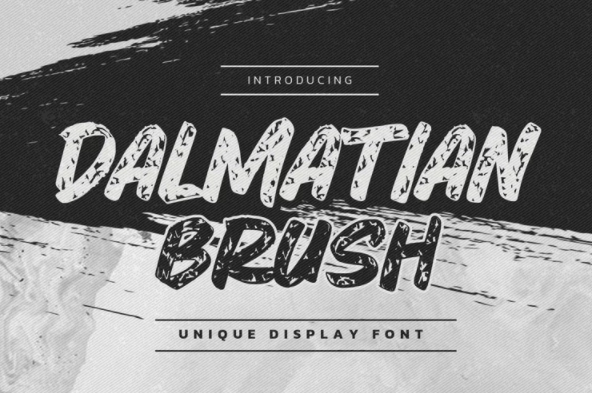
[Fontbundles] Dalmatian Brush Font (2022)
Π’ΠΎΡ‚ ΠΈ наш Π½ΠΎΠ²Ρ‹ΠΉ ΡˆΡ€ΠΈΡ„Ρ‚ Dalmatian Brush это ΡƒΠ½ΠΈΠΊΠ°Π»ΡŒΠ½Ρ‹ΠΉ ΡˆΡ€ΠΈΡ„Ρ‚, ΠΊΠΎΡ‚ΠΎΡ€Ρ‹ΠΉ ΠΏΠΈΡˆΠ΅Ρ‚ΡΡ Π½Π΅ΠΏΡ€ΠΈΠ½ΡƒΠΆΠ΄Π΅Π½Π½ΠΎ ΠΈ быстро. Π­Ρ‚ΠΎ аутСнтичная ΠΊΠΈΡΡ‚ΡŒ ΠΈ ΡΡ‚ΠΈΠ»ΡŒΠ½Ρ‹ΠΉ ΡΡ‚ΠΈΠ»ΡŒ.
Π­Ρ‚ΠΎΡ‚ ΡˆΡ€ΠΈΡ„Ρ‚ создан Π²Ρ€ΡƒΡ‡Π½ΡƒΡŽ с ΠΏΠΎΠΌΠΎΡ‰ΡŒΡŽ кистСй Π² Procreate. Π­Ρ‚ΠΎΡ‚ ΡˆΡ€ΠΈΡ„Ρ‚ ΠΎΡ‚Π»ΠΈΡ‡Π½ΠΎ ΠΏΠΎΠ΄Ρ…ΠΎΠ΄ΠΈΡ‚ для Π²Π°ΡˆΠΈΡ… творчСских ΠΏΡ€ΠΎΠ΅ΠΊΡ‚ΠΎΠ², Ρ‚Π°ΠΊΠΈΡ… ΠΊΠ°ΠΊ водяной Π·Π½Π°ΠΊ Π½Π° Ρ„ΠΎΡ‚ΠΎΠ³Ρ€Π°Ρ„ΠΈΠΈ, ΠΈ идСально ΠΏΠΎΠ΄Ρ…ΠΎΠ΄ΠΈΡ‚ для Π»ΠΎΠ³ΠΎΡ‚ΠΈΠΏΠΎΠ² ΠΈ Π±Ρ€Π΅Π½Π΄ΠΈΠ½Π³Π°, Ρ„ΠΎΡ‚ΠΎΠ³Ρ€Π°Ρ„ΠΈΠΈ, ΠΏΡ€ΠΈΠ³Π»Π°ΡˆΠ΅Π½ΠΈΠΉ, водяных Π·Π½Π°ΠΊΠΎΠ², Ρ€Π΅ΠΊΠ»Π°ΠΌΡ‹, Π΄ΠΈΠ·Π°ΠΉΠ½Π° ΠΏΡ€ΠΎΠ΄ΡƒΠΊΡ‚ΠΎΠ², канцСлярских принадлСТностСй, свадСбных Π΄ΠΈΠ·Π°ΠΉΠ½ΠΎΠ², этикСток, ΡƒΠΏΠ°ΠΊΠΎΠ²ΠΊΠΈ ΠΏΡ€ΠΎΠ΄ΡƒΠΊΡ‚ΠΎΠ², ΡΠΏΠ΅Ρ†ΠΈΠ°Π»ΡŒΠ½Ρ‹Ρ… мСроприятий ΠΈΠ»ΠΈ всСго, Ρ‡Ρ‚ΠΎ Ρ‚Ρ€Π΅Π±ΡƒΠ΅Ρ‚ рукописного вкуса.
Π­Ρ‚ΠΎ СстСствСнный рукописный ΡˆΡ€ΠΈΡ„Ρ‚. Π­Ρ‚ΠΎΡ‚ ΡˆΡ€ΠΈΡ„Ρ‚ Ρ€ΡƒΡ‡Π½ΠΎΠΉ Ρ€Π°Π±ΠΎΡ‚Ρ‹ сдСлаСт ваш Π΄ΠΈΠ·Π°ΠΉΠ½ красивым ΠΈ СстСствСнным. Он идСально ΠΏΠΎΠ΄Ρ…ΠΎΠ΄ΠΈΡ‚ для любого дизайнСрского ΠΏΡ€ΠΎΠ΅ΠΊΡ‚Π°, ΠΊΠ°ΠΊ ΠΏΡ€ΠΈΠ³Π»Π°ΡˆΠ΅Π½ΠΈΠ΅, Π»ΠΎΠ³ΠΎΡ‚ΠΈΠΏ, ΠΎΠ±Π»ΠΎΠΆΠΊΠ° ΠΊΠ½ΠΈΠ³ΠΈ, рСмСсло ΠΈΠ»ΠΈ Π»ΡŽΠ±Ρ‹Π΅ Ρ†Π΅Π»ΠΈ Π΄ΠΈΠ·Π°ΠΉΠ½Π°.
Π’ΠΎ Π΅ΡΡ‚ΡŒ Dalmatian Brush - это сильная характСристика Π±ΠΎΠ»Π΅Π΅ СстСствСнного Π²ΠΈΠ΄Π° для вашСго тСкста с Π±ΠΎΠ»Π΅Π΅ соврСмСнным Π²ΠΈΠ΄ΠΎΠΌ для вашСго тСкста.